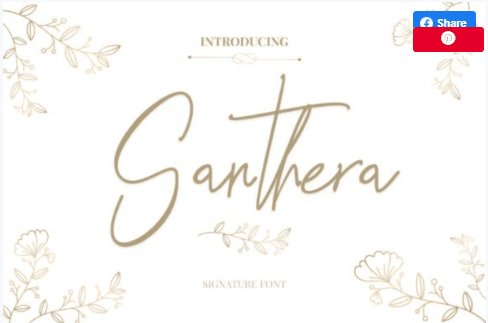
Santhera Font
Santhera - модный и легкий рукописный шрифт. Поддайтесь его изысканному стилю и используйте его для создания великолепных свадебных приглашений, красивых канцелярских принадлежностей, привлекательных постов в социальных сетях и многого другого!